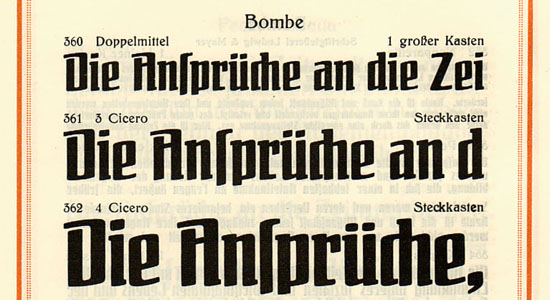
Schaftstiefelgrotesk?
Das ist nicht die Tannenberg (am B zu erkennen) – aber was dann?
Ich kann sie bei meinen Mustern von Neu-Gotischen auch nicht finden.
Könnte das nicht handgemacht sein?
Ich hatte mal eine Feldausgabe der Wehrmacht für Kalligraphie mit ca. 120 Seiten Mustern, Anleitungen usw. Und dabei waren erstaunlich viele alte Firmenschriftzüge in diesem Charakter. Könnte es sein, daß diese Technik in dieser Epoche viel öfter eingesetzt wurde als wir es uns heute vorstellen?
Das ist gut möglich. Die Form der Buchstaben ist ja auch mit Geodreieck und Lineal gut „nachzuzeichnen“.
die marienburg von genzsch & heyse war mit bis dato unbekannt.
vielleicht können wir mal alle schlichten gotischen stiefelschriften
nennen, dann habe wir die mal alle zur hand. oder noch besser:
ralf macht da mal einen wikieintrag, oder gibts den schon?
marienburg fett
eßt deutsches obst! :shock:
marienburg schmalfett
gibts auch noch mager.
und dann noch diese hier:
der name ist programm »BOMBE« von ludwig meyer.
hat da einer mehr infos? erstguß? von wem ist die?
Schau an, die Bombe kam mir bekannt vor:
Ist so etwas, wenn kein "Inspiriert durch..." dann:
- peinlich
- ein Fauxpas
- völlig normal, weil letztendlich jeder Schriftentwerfer bewußt oder unbewußt inspiriert wird von anderen Schriften
:?:
Beim ersten Betrachtung gefällt mir die Bombe sehr. Das wird heute noch eine gute Font-Name, denk ich. Oder im englischen "Bomb"…
"Hey, wow! What is that typeface? That font is da BOMB!"
die marienburg von genzsch & heyse war mit bis dato unbekannt.
vielleicht können wir mal alle schlichten gotischen stiefelschriften
nennen, dann habe wir die mal alle zur hand. oder noch besser:
ralf macht da mal einen wikieintrag, oder gibts den schon?
marienburg fett
eßt deutsches obst! :shock:
marienburg schmalfett
gibts auch noch mager.
Die fette »Marienburg« scheint m.E. identisch mit der fette »Deutschland« von Berthold zu sein. Ich habe davon zwar den Font (von Helzel) aber kein Original-Schriftmuster.
Die Idee mit dem Wikieintrag find' ich gut. Am Sammeln beteilige ich mich (meine Fonts sind im ersten Eintrag dieses Themas– ohne Namensnennung – aufgeführt).
die marienburg von genzsch & heyse war mit bis dato unbekannt.
vielleicht können wir mal alle schlichten gotischen stiefelschriften
nennen, dann habe wir die mal alle zur hand. oder noch besser:
ralf macht da mal einen wikieintrag, oder gibts den schon?
marienburg fett
eßt deutsches obst! :shock:
marienburg schmalfett
gibts auch noch mager.
Jetzt, wo Du es sagst:
Das kann ich bestätigen. Ich habe vor Jahren einmal eine "Marienburg" gekauft, sie selbst aber als "Deutschland" klassifiziert. Bis sich dann ergab, daß sie identisch sind.
Das mit diesem Wiki-Dings würde ich unterstützen wollen.
Gern auch mit Mustern von meiner Schriftensammlung :)
Apropos "eßt deutsches obst!"
Sinnvoller, als Orangen oder sonstiges Obst aus Israel oder Südafrika einzufliegen und CO2 zu verblasen, wäre das eigentlich schon.
„Gedenke deiner Ahnen.
Sei Deutsch in Wort und Tat.
Iß Äpfel – nicht Bananen.
Üb’ Treue – nicht Verrat.“
:twisted: (Bitte in der »Tannenberg« vorstellen … oder in der »Deutschland«)
Flosemann
... vielleicht können wir mal alle schlichten gotischen stiefelschriften nennen, dann habe wir die mal alle zur hand. oder noch besser: ralf macht da mal einen wikieintrag, oder gibts den schon?
Ich hoffe Ralf ist das recht. Ich hab’ mal mit dem Wiki-Eintrag angefangen, weil ich auch schon am Sammeln bin:
Schlichte Gotisch
Kann ja jeder selber mit ergänzen.
Eine Frage habe ich aber dazu. Meinst Du alle gebrochene Groteskschriften oder nur die, die einige (Wilberg, Kapr, ...?) als Schaftstiefelgrotesk bezeichnen. Wie ich verstanden habe, werfen die die es seriös meinen, nicht alles in einen Topf.